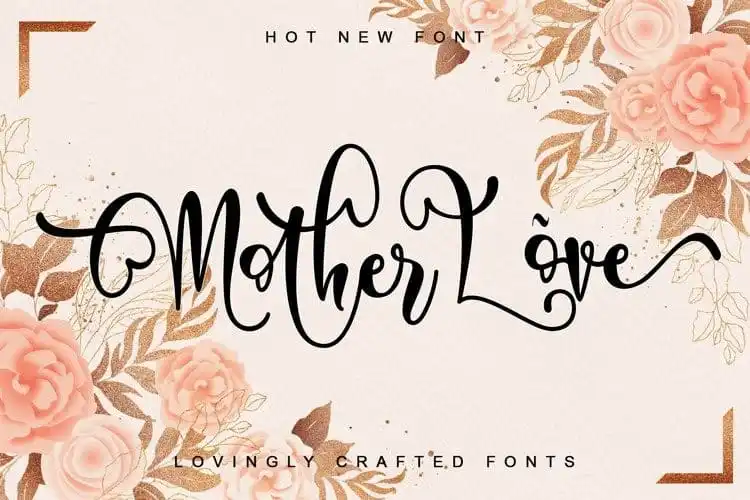
A Mother Love Calligraphy Font é uma elegante escolha para designers que desejam dar vida a suas criações com estilo próprio. Este script elegante foi criado pelo talentoso designer letterara e traz caracteres bem equilibrados, proporcionando um visual atraente tanto em projetos pessoais quanto profissionais. Seu design casual e rápido oferece uma versatilidade incrível, ideal para qualquer projeto de gráfica ou arte digital. Com uma característica chamada PUA, você pode acessar facilmente todos os maravilhosos caracteres e swashes que a fonte tem a oferecer. Além disso, ela inclui várias funções especiais como alternativas de caractere e ligaturas, tornando-a perfeita para criar designs inovadores que realmente chamam atenção. Seja em sua próxima peça de arte ou projeto gráfico, essa fonte será definitivamente um acréscimo a qualquer conjunto criativo.